ბოლო 5 წლის მანძილზე ყველაზე მასშტაბური გაფართოების მომსწრენი ვხდებით, რადგან Adobe Fonts-ის კოლექციას 1500 შრიფტი დაემატა— კლასიკურ და თანამედროვე ფონტებს აერთიანებს, მათ შორის ყველაზე ხშირად გამოყენებულსაც შრიფტებს დიზაინის ისტორიაში. აქ Helvetica, Gotham, Avenir, Times New Roman, Arial, და Proxima Nova-ც შეგხვდებათ.
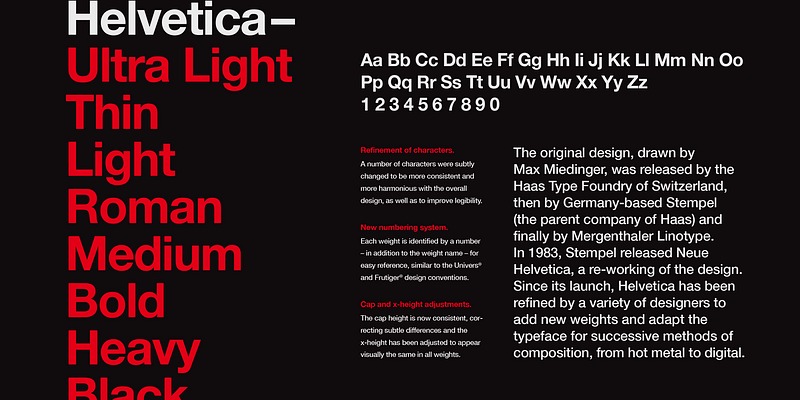
შრიფტების უმეტესობა Monotype-თან თანამშრომლობით შეიქმნა, რაც ბრენდის 750 ფონტის Adobe-ის ეკოსისტემაში გაერთიანებას მოიცავს ისეთი ცნობილი სახელებით, როგორებიცაა, ზემოთ ხსენებულ Helvetica-ს, Gotham-სა და Avenir-თან ერთად, Benton Modern და FF DIN.
რაც შეეხება ენების მხარდაჭერას, იგი ახლა არაბულს, ჰინდისა და იაპონურსაც მოიცავს, რითაც მზარდ ინტერესს ასახავს გლობალური ხელმისაწვდომობისა თუ მრავალენოვანი დიზაინის მიმართ.
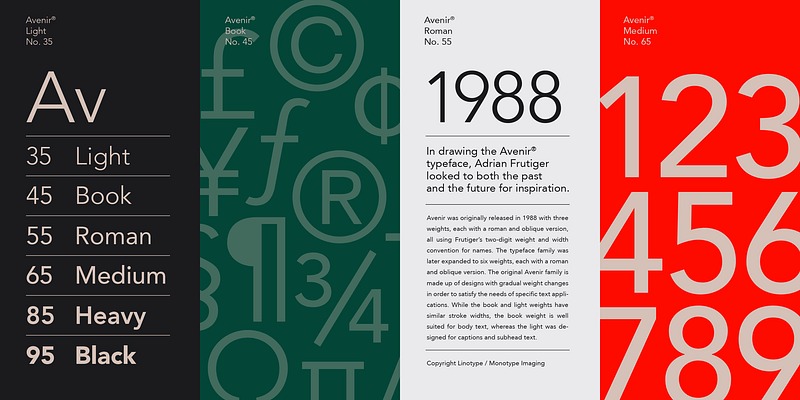
რაღა თქმა უნდა, ამ ჩამონათვალში Microsoft-ის Times New Roman და Arial-იც გვხვდება, რითაც თანამედროვე ნამუშევრებში კლასიკის შეტანას გვთავაზობენ: